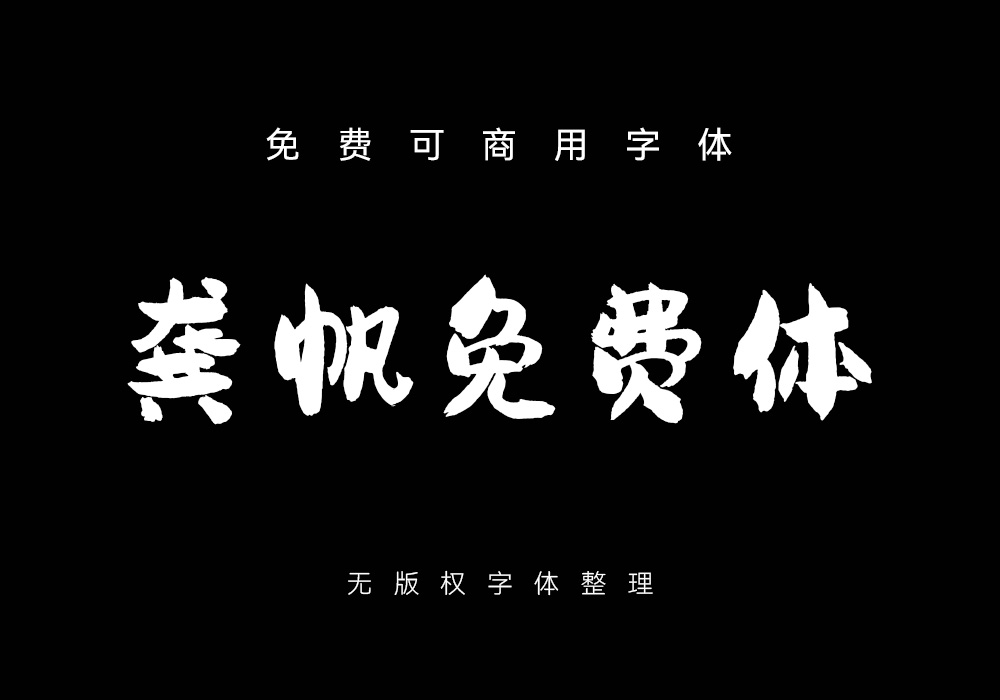
龚帆免费体:免费可商用毛笔字体下载 2021-06-26 7.23k 龚帆免费体是视觉坊发布的一款高质量的免费商用毛笔字体,这款字体含3000+常用的简体中文字形,能满足一般的设计需求。 资源下载链接立即下载(提取码: 84is)复制下载地址2立即下载下载地址失效请联系右侧客服补链文件类型:TTF资源大小:6MB兼容软件:Win/Mac商业许可:免费可商用 常见问题 素材可以商用吗,会不会有版权问题?除特殊说明之外,本站所有素材仅限学习交流,不可商用! 百度网盘下载慢怎么办?国内只有在百度网盘存放资源相对靠谱,基本不会出问题,如果是非会员建议使用天翼云盘下载资源,完全免费不限速。 原文链接:https://kusheji.com/fonts/19421.html,转载请注明出处。 0 2 可商用字体